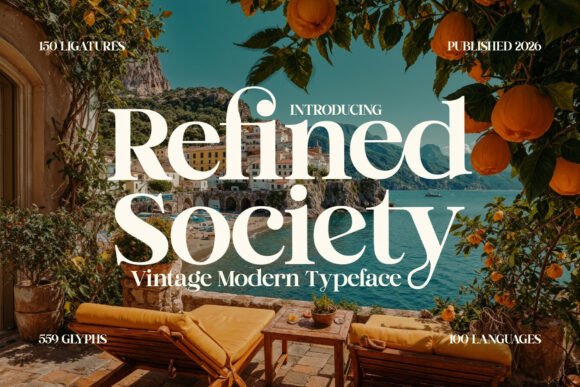
Refined Society
POD(์ฃผ๋ฌธํ˜• ์ธ์‡„) ์ œํ’ˆ, ๊ฒฐํ˜ผ์‹ ์ดˆ๋Œ€์žฅ ๋˜๋Š” ์†Œ์…œ ๋ฏธ๋””์–ด ๊ทธ๋ž˜ํ”ฝ์„ ๋งŒ๋“ค ๋•Œ Refined Society๋Š” ์ด์ƒ์ ์ธ ์„ ํƒ์ž…๋‹ˆ๋‹ค.